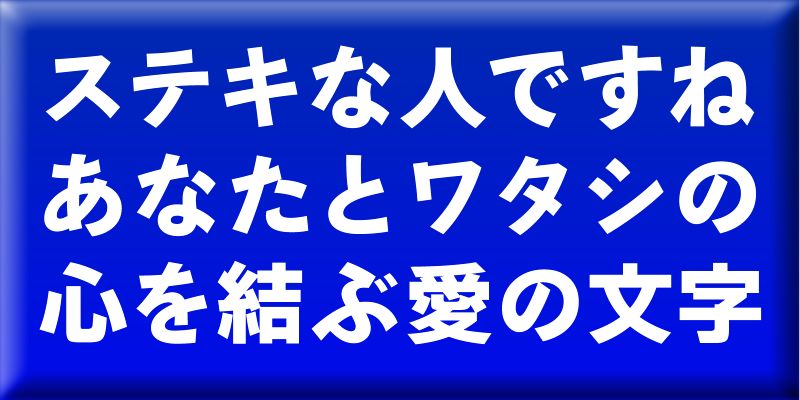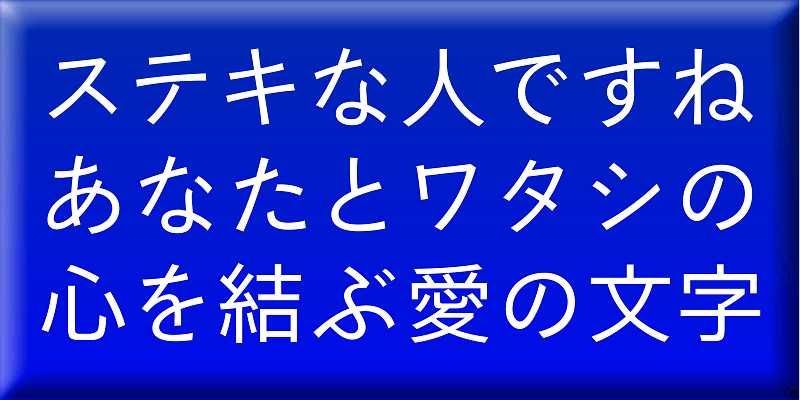
Ihre Kana-Zeichen haben traditionelle Formen, die wunderschön bearbeitet und bereichert wurden. Gepaart mit modernen Kanji-Ideogrammen sorgt BukotohRuika-07 für ein frisches Aussehen der Satzergebnisse.